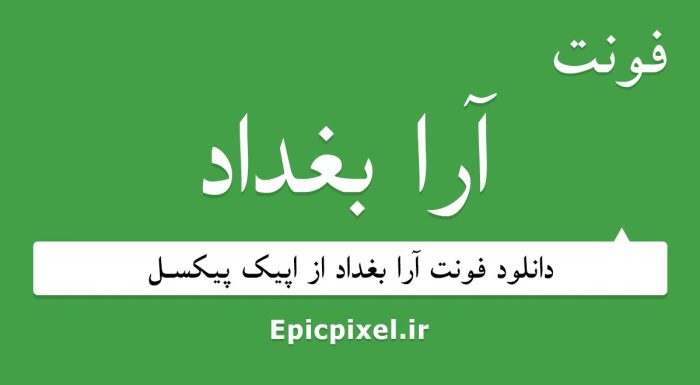
فونت آرا بغداد عربی فارسی
فونت آرا بغداد، با طراحی منحصربه فرد خود، پلی بین زیبایی خط عربی و خوانایی خط فارسی ایجاد کرده است. این فونت، با الهام از خطوط سنتی بغدادی که در نسخه های قدیمی قرآن و متون نفیس دیده می شود، حس اصالت و قدمت را به نوشته های شما می بخشد. در عین حال، ساختار حروف به گونه ای طراحی شده که برای خوانندگان فارسی زبان نیز بسیار روان و دلنشین باشد و از خستگی چشم در متون طولانی جلوگیری می کند.
ویژگی بارز این فونت، تعادل هنرمندانه بین فرم های منحنی و خطوط مستقیم است؛ این ویژگی، هم زیبایی بصری چشم نوازی به متن می بخشد و هم خوانایی آن را در اندازه های مختلف، تضمین می کند. ظرافت در جزئیات، مانند شکل نقاط و اتصالات حروف، به آرا بغداد شخصیتی متمایز داده و آن را برای استفاده در طراحی های مدرن و سنتی، از جمله جلد کتاب، پوستر، وب سایت و حتی اپلیکیشن های موبایل، ایده آل ساخته است.
شبیه فونت بی نازنین میمونه اما برای متن کتاب و مقاله میشه ازش استفاده کرد